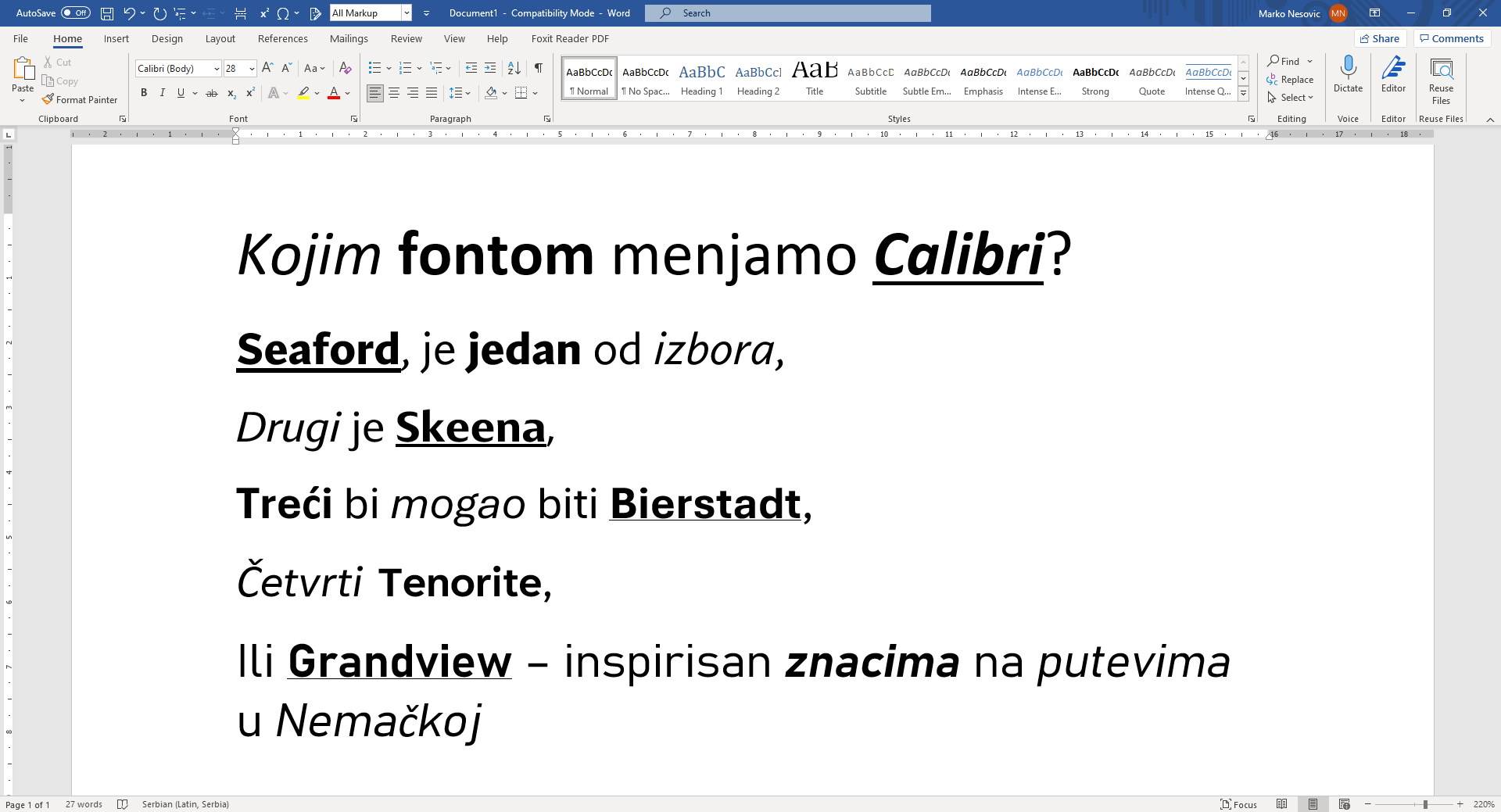
Omiljeni font koji je skoro 15 godina bio prepoznatljiv znak Office paketa naredne godine će dobiti svoju zamenu, a Microsoft želi da i vi pomognete u izboru.
Iako vam Word nudi preko 700 raspoloživih fontova, skoro 15 godina je Calibri bio podrazumevani font za Office paket. Microsoft je odlučio da je konačno vreme za promenu i da će od naredne godine Office dobiti svoj novi defaultfont.
Microsoft je počeo sa sakupljenjempovratnih informacija za nove predložene sans-seriffontove. Predlozi obuhvataju nekoliko različitih stilova, uključujući tradicionalne, moderne, pa i zanimljivi Grandview font, inspirisan nemačkim znacima pored puta.
Seaford je font koji deluje najsličniji serif fontovima, a dizajneri kažu da je inspiracija došla od izgleda starih stolica, sa idejom da se deo klasike udahne u fontove. Seaford je jedan od fontova koji je veoma prijatan za čitanje dugih dokumenata, i zbog toga ima velike šanse da postane novi Calibri,
Skeena ima interesantne varijacije u tankim i debelim delovima slova, sa veoma prepoznatljivim krivinama na nekim slovima kao što su S, A ili J.
Bierstadt vuče korene iz švajcarske tipografije iz sredine 20 veka, sa veoma odsečnim završetkom slova, ali i sa suptilnim krivinama kojima se izbegava rigitdnost ovog tipa fontova. Dizajner fonta koristi sans serifosnovu (Helvetica je jedan od najpoznatijih fontova ove porodice) sa sličnostima sa Microsoft Arial fontom, praveći kombinaciju rigidnih i blagih, dopadljivih linija.
Tenorite je najtradicionalniji font od pet predloženih, i podseća na modernu verzijuTimes New Romanfonta od pre desetak godina, sa širokim slovima, akcentima i jasnom interpunkcijom. Možda će biti jedan od favorita zbog prepoznatljivosti fonta iz čijih korena vuče svoj dizajn.
Grandview deluje kao najupečatljiviji od svih i svoju inspiraciju izvlači iz starih nemačkih železničkih i znakova pored puta. Kao i kod znakova, njegova najveća prednost je jasna čitljivost, sa finim podešavanjima tu i tamo kako bi bio dobar za čitanje dugih dokumenata.
Kao što možete videti, svi ovi fontovi su već dostupni u Office 365 paketu, pa ih mpožete odabrati i probati, a Microsoft će organizovati ankete i na osnovu povratnih informacija izabrati novi podrazumevani font.